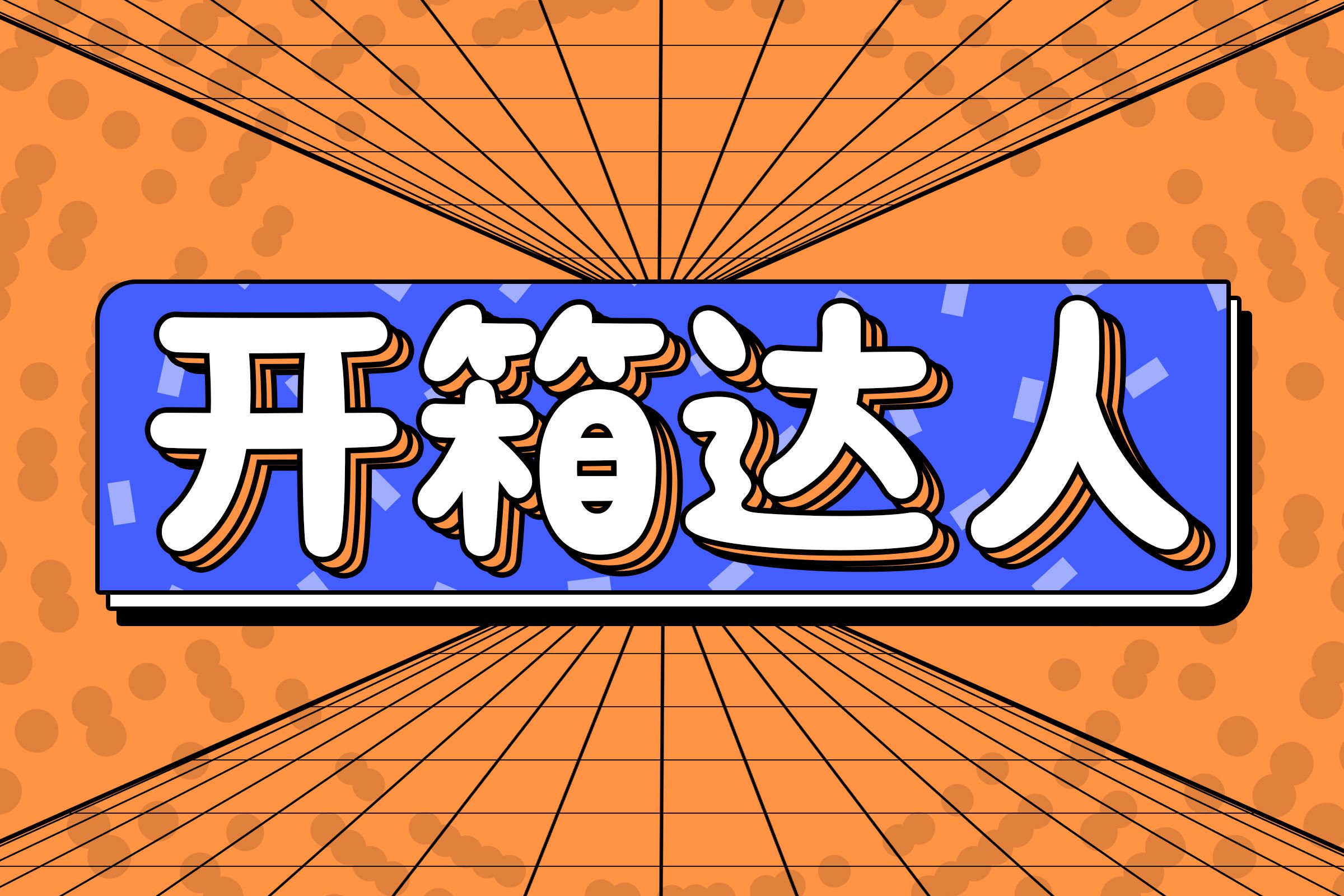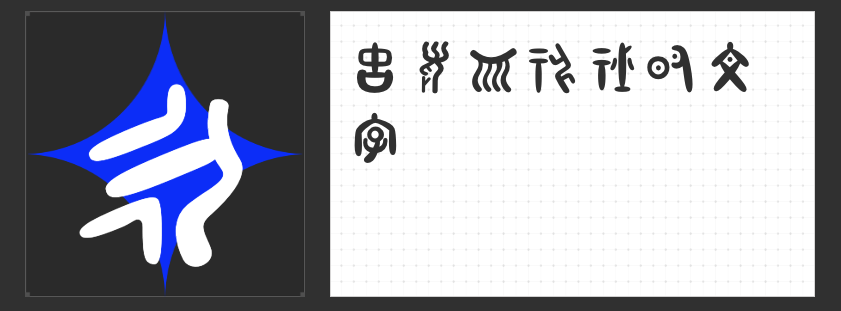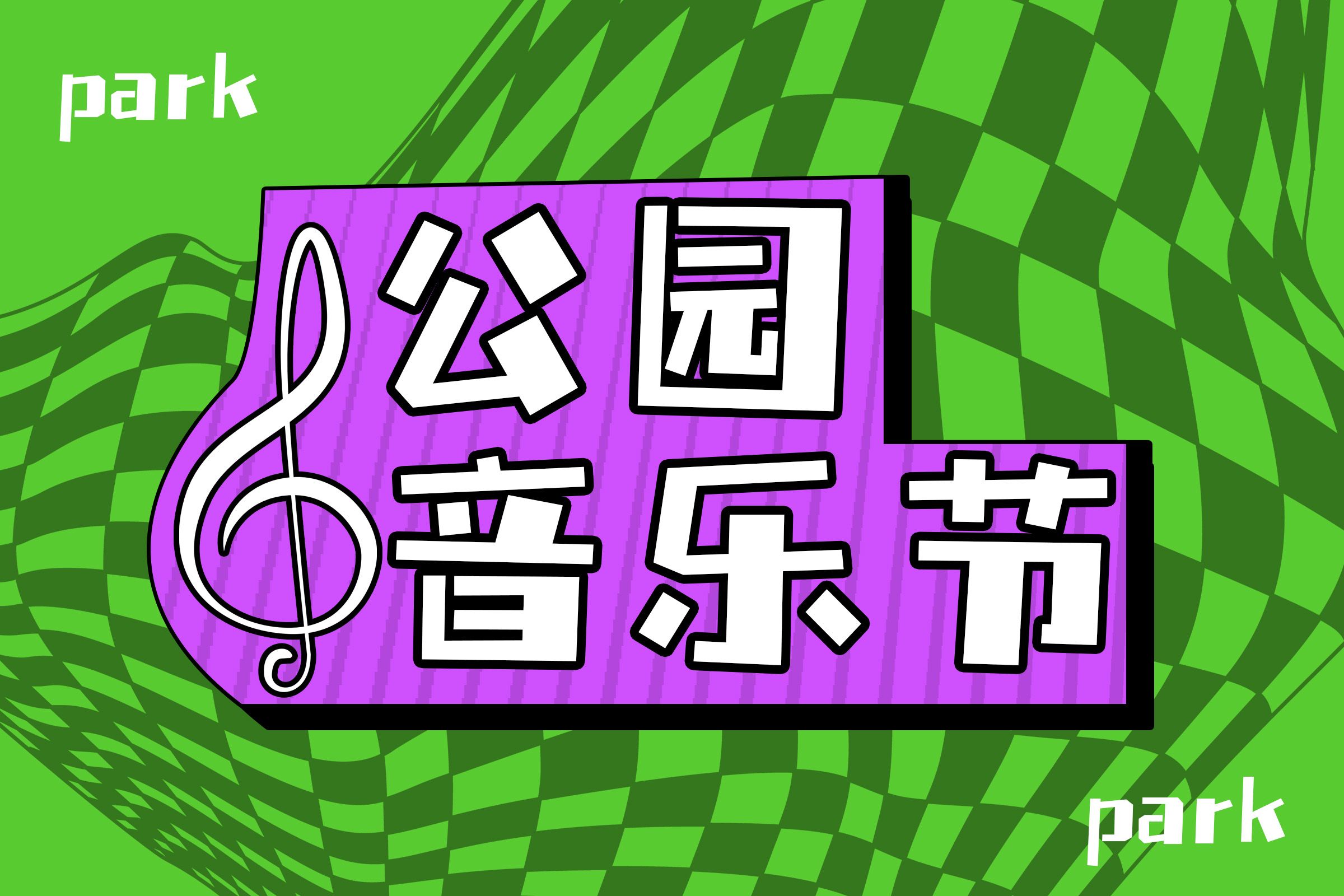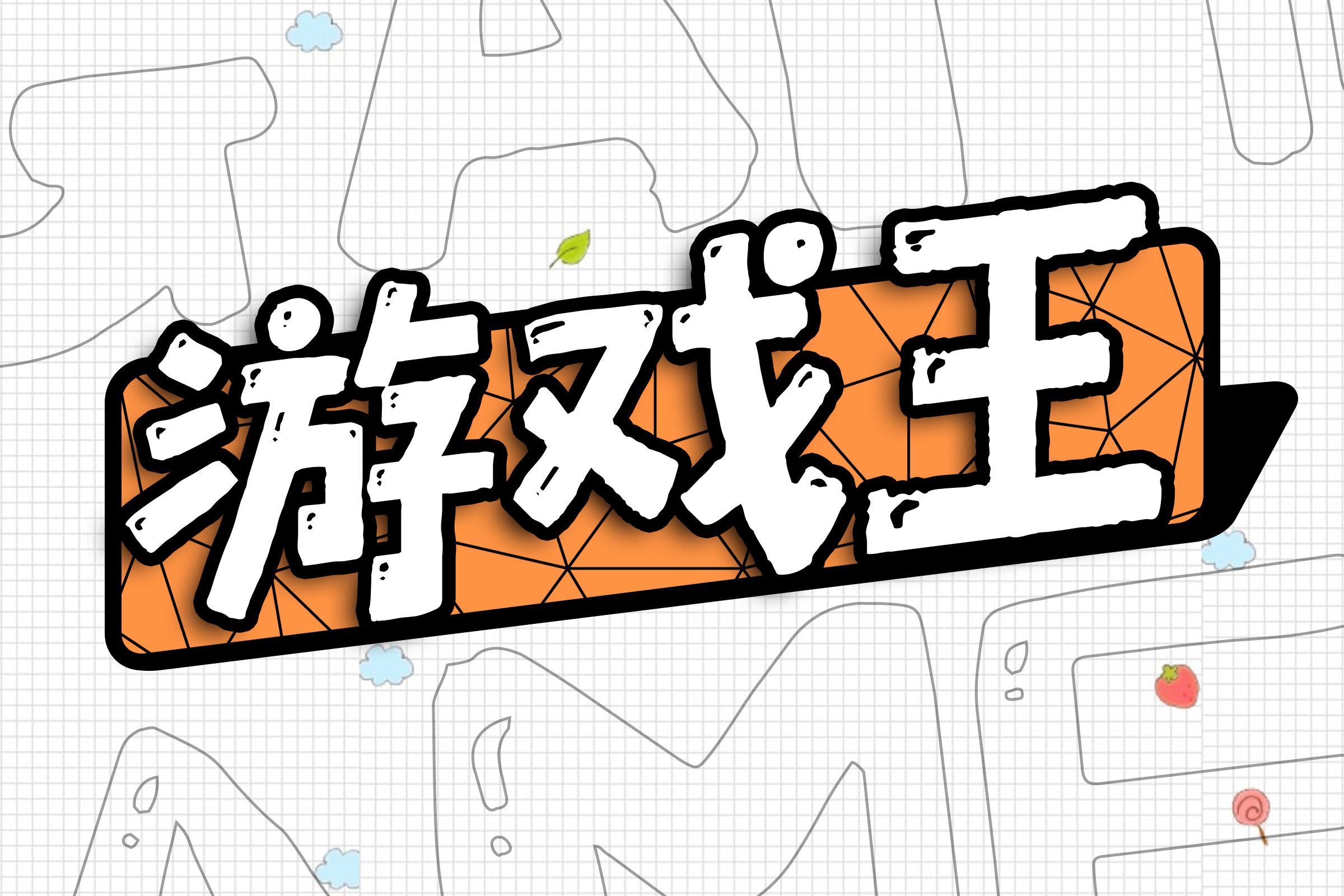
“喵字馆”系列创意字体推荐:为你的设计增添无限可能
在设计领域,字体不仅是传递信息的工具,更是展现创意与个性的载体。今天,为大家推荐四款来自“喵字馆”系列的创意字体,它们各具特色,能够满足不同设计场景的需求。
♠︎ 1.喵字字幕体 ♠︎
专为新媒体行业量身打造的定制级细分字库。这款字体结合了现代感与易读性,字形设计大胆开放,摒弃了传统字库的严肃感,巧妙融入年轻化元素,非常适合当下新媒体内容创作者的需求。无论是视频字幕、社交媒体文案还是网络广告,喵字字幕体都能为你的作品增添一份独特的视觉魅力。
♣︎ 2.喵字冻柠体 ♣︎
专为海报设计领域打造的定制级细分字库。灵感源自夏日柠檬的清爽,将现代简约与时尚元素完美融合。冻柠体的字形结构均衡而富有张力,笔画间的粗细变化模拟了冰块碰撞的动态美感,赋予文字独特的视觉冲击力。无论是商业海报、活动宣传还是品牌展示,喵字冻柠体都能让你的海报瞬间脱颖而出。
♥︎ 3.喵字绘本体 ♥︎
定位于绘本市场的定制级字库产品。这款字体结合了手写字体的风格特点与创意字体的间架结构,嫁接出一种具备“工业感”的“手绘”风格。喵字绘本体能够帮助绘本设计师丰富字体选择,为绘本作品增添一份独特的艺术气息。无论是儿童绘本、插画书籍还是艺术画册,喵字绘本体都能为你的作品带来不一样的视觉体验。
♦︎ 4.童心甲骨文 ♦︎
定位于儿童教育行业的细分字库产品。整体风格轻盈、圆润,带有强烈的手写感和卡通特点,非常适合用于教育相关的素材和物料。童心甲骨文的字形清晰可辨,便于儿童初学者识字和书写。在教室、教材、海报等教育资源中使用,童心甲骨文都能为孩子们带来乐趣和启发,让他们更加热爱学习。